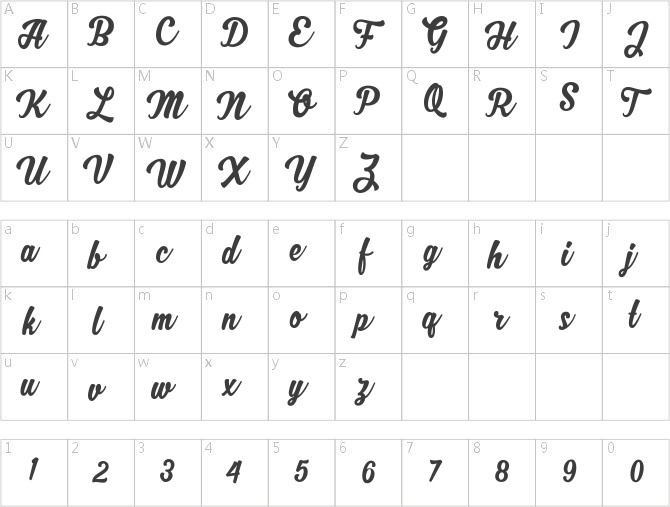
MJF Zhafira Demo 詳情頁
MJF Zhafira Demo字體字庫是一款讓人賞心悅目、百看不厭的英文字體,適合各類廣告和產(chǎn)品包裝設(shè)計(jì)應(yīng)用,字體大小0.1MB,格式為ttf字體,上傳用戶是17199970014,作者/版權(quán)方為未知